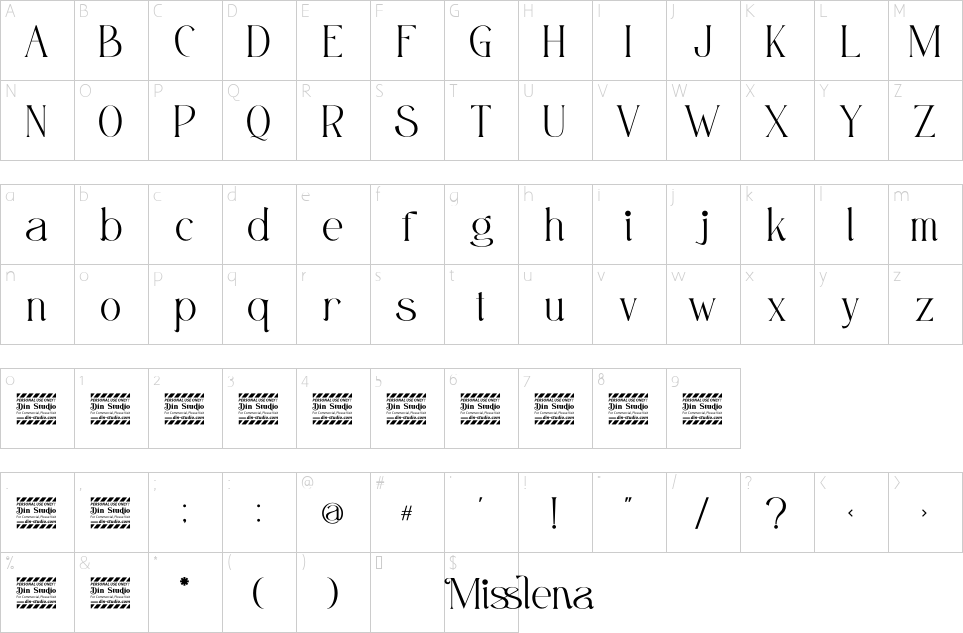
A fonte Misslena é uma delícia para os olhos, perfeita para qualquer projeto gráfico. Desenvolvida pela Din Studio, ela foi projetada para aqueles que buscam uma fonte versátil e elegante. Com 3.611 downloads, é um recurso que merece atenção. A Misslena é uma fonte clean e agradável, ideal para textos legíveis em qualquer tamanho. Suas linhas suaves e harmoniosas garantem que sua marca seja sempre forte e profissional. Com a Misslena, transforme qualquer design em algo único e encantador. Que tal dar uma chance a essa fonte? Sem dúvida, ela merece o seu tempo.